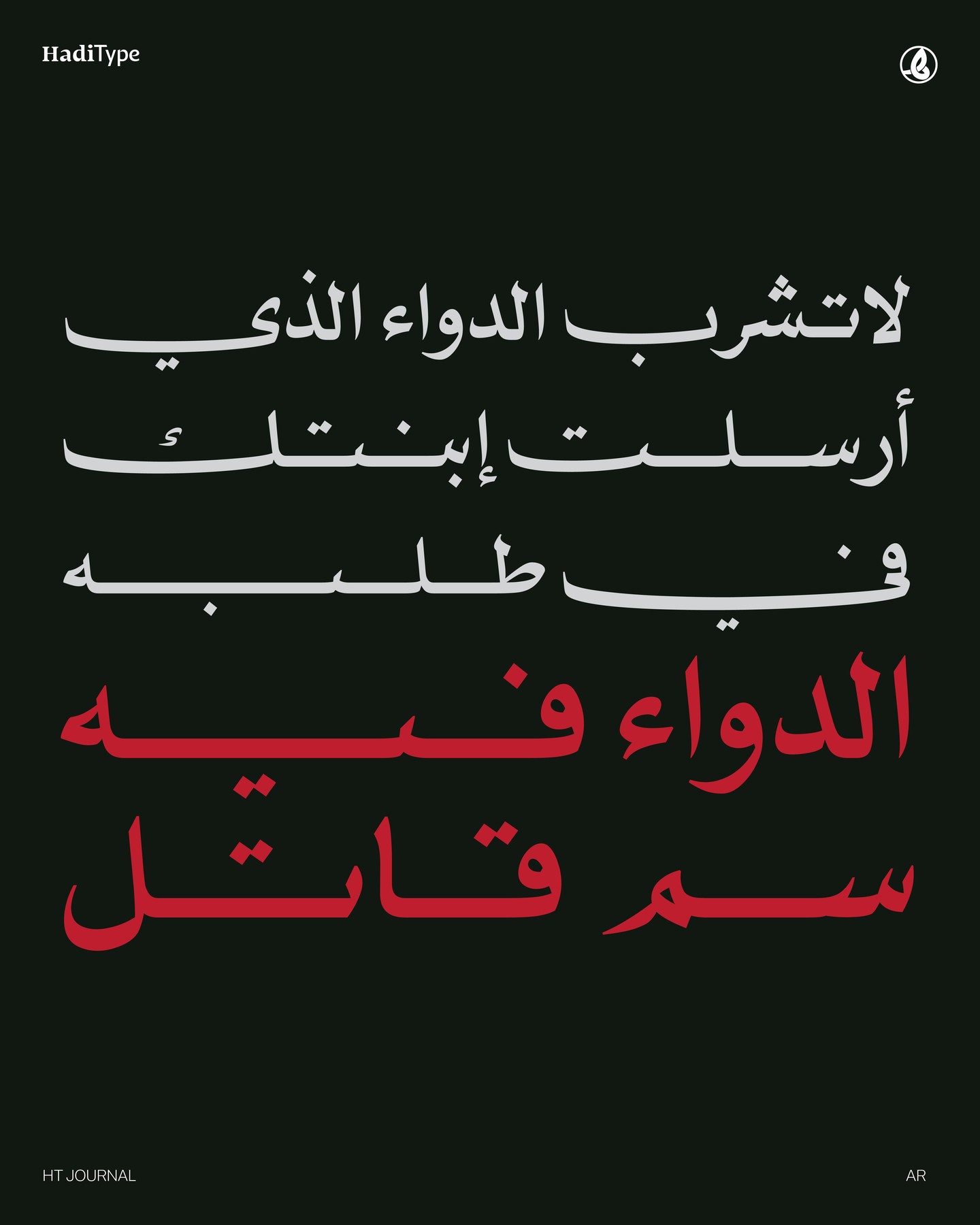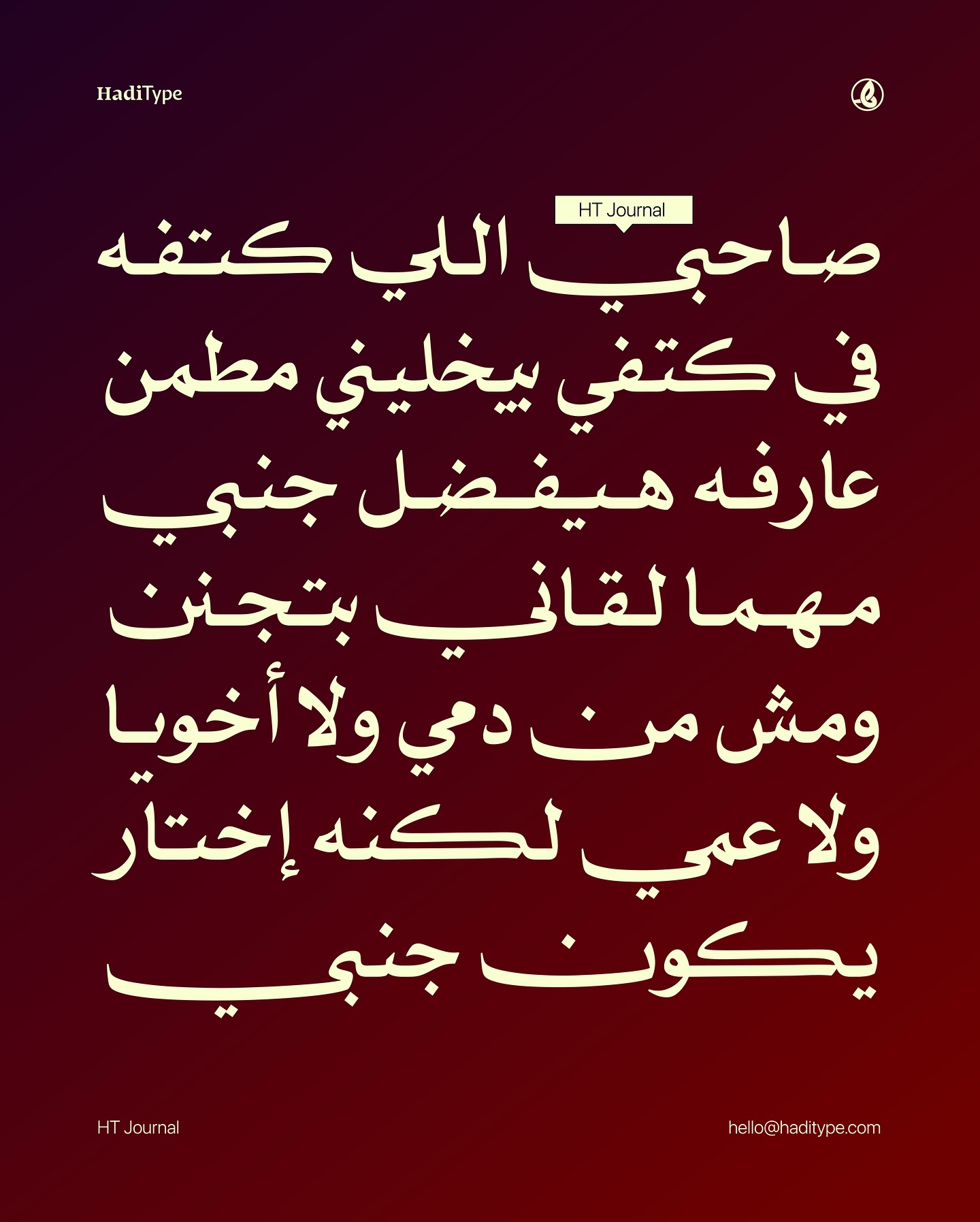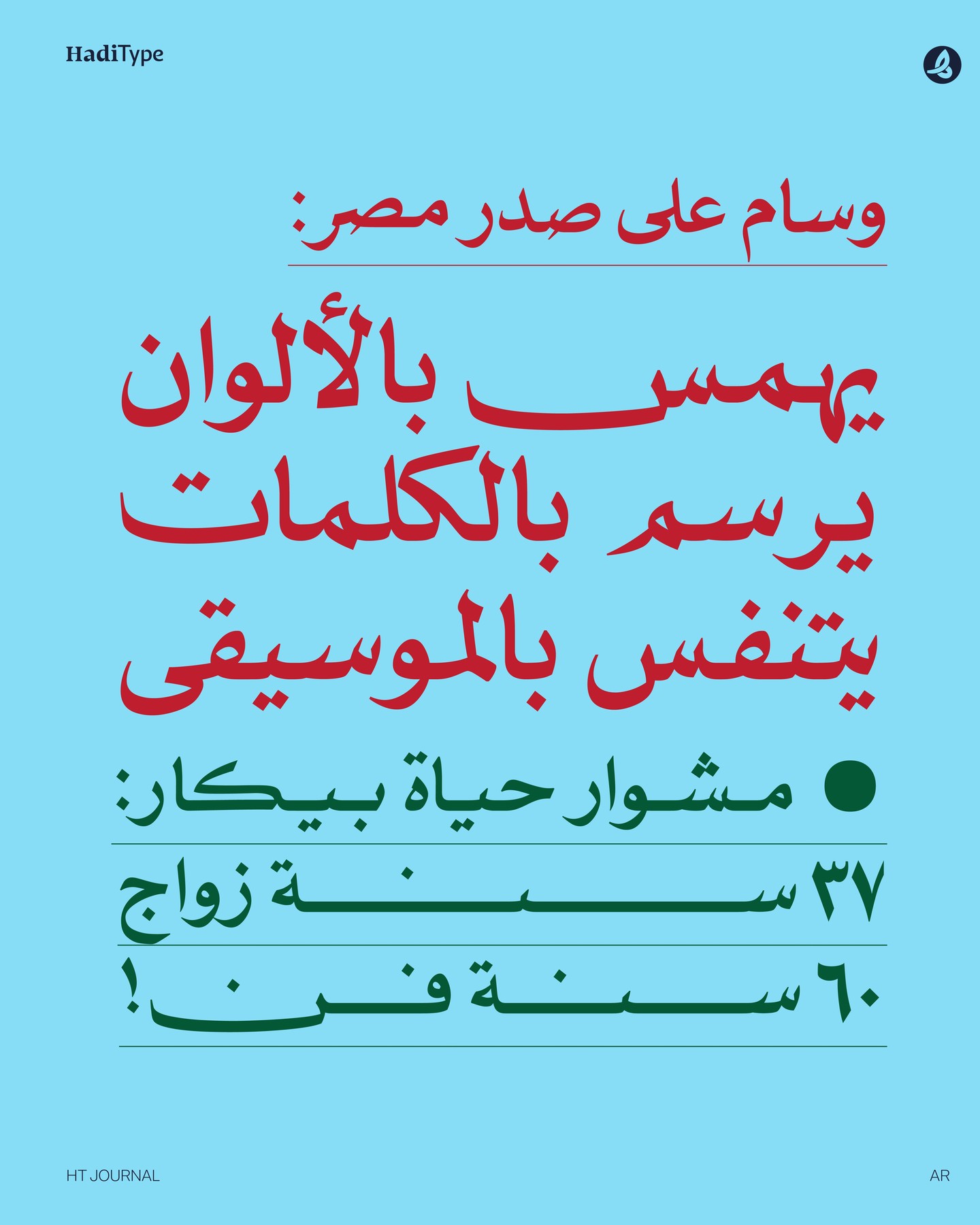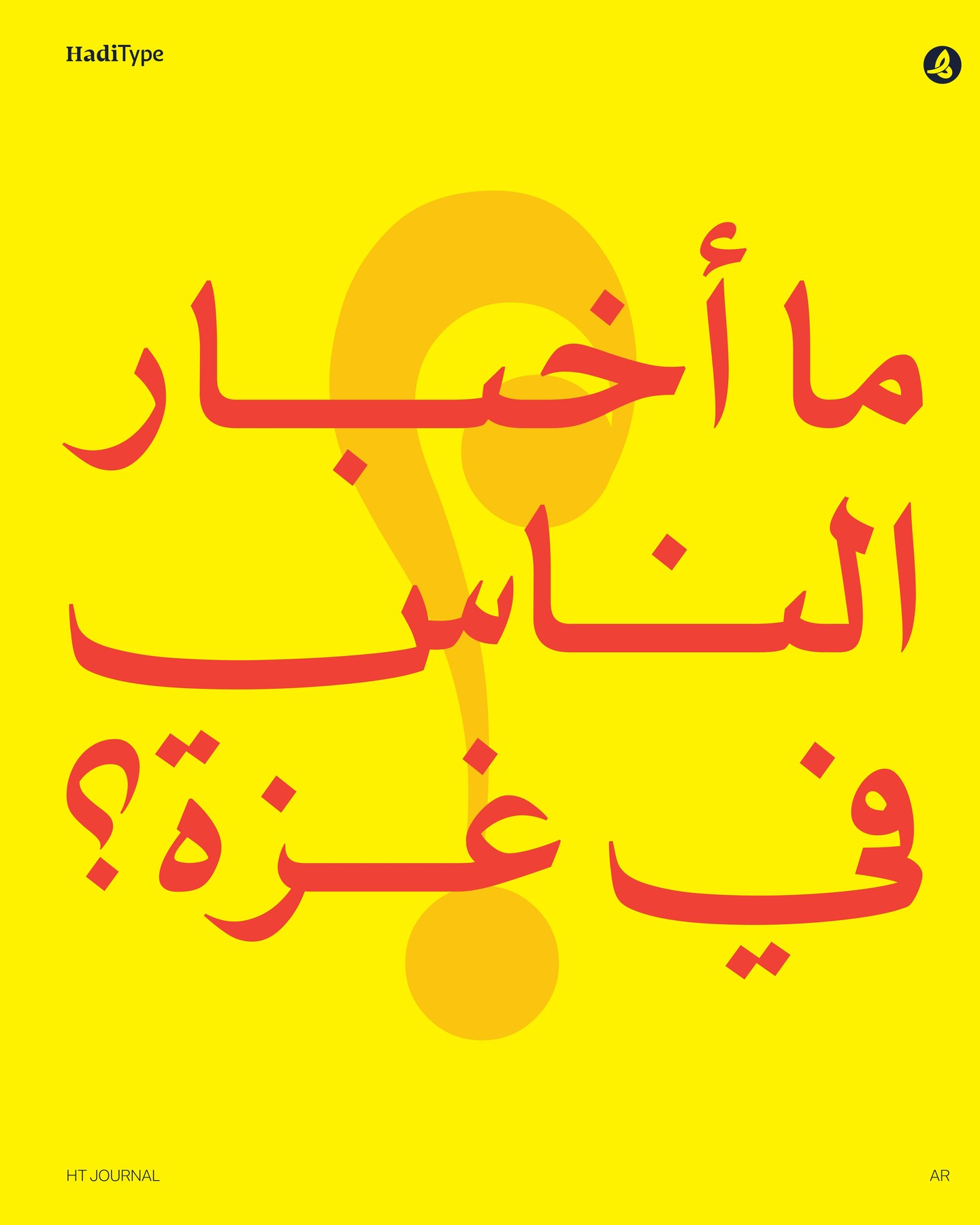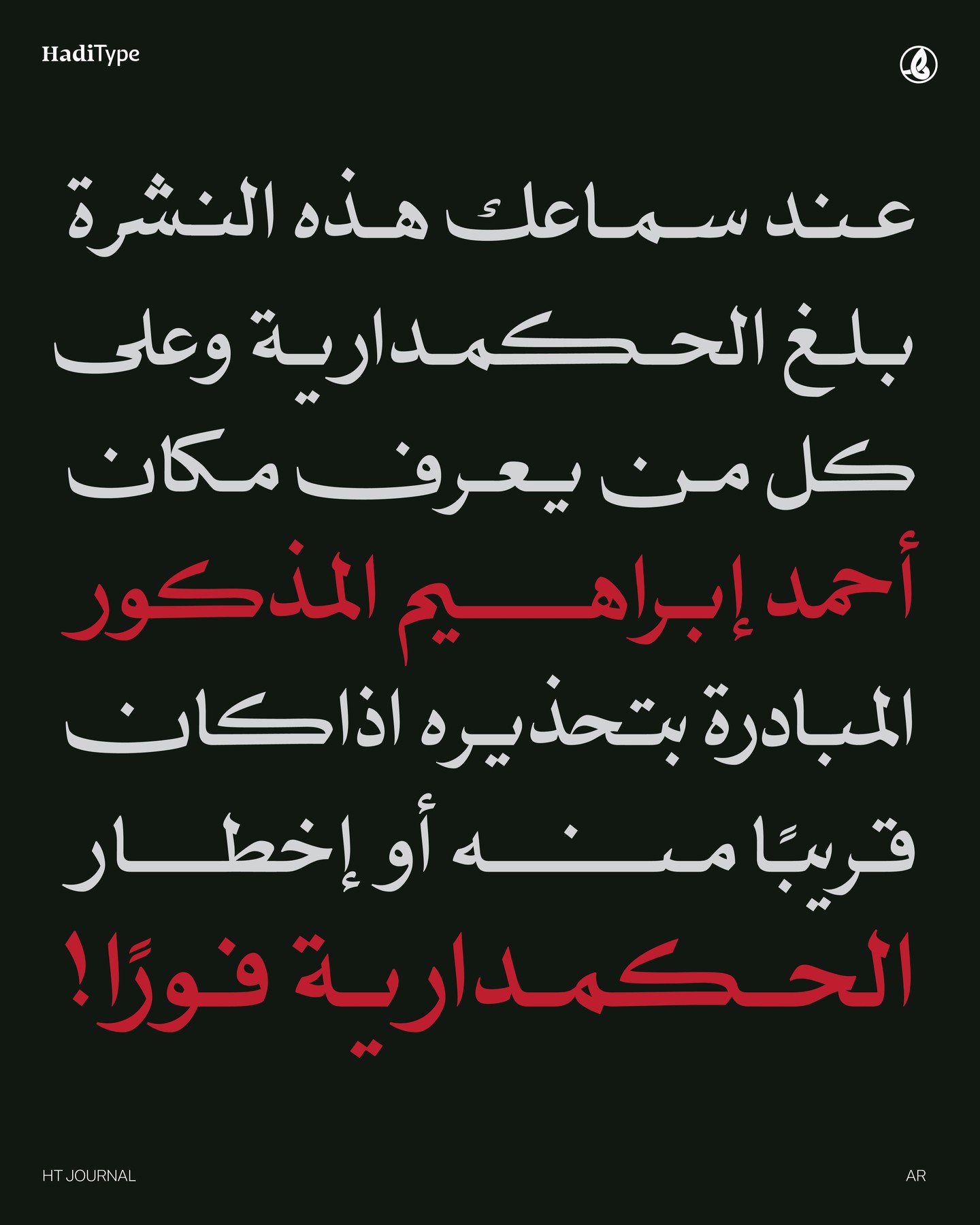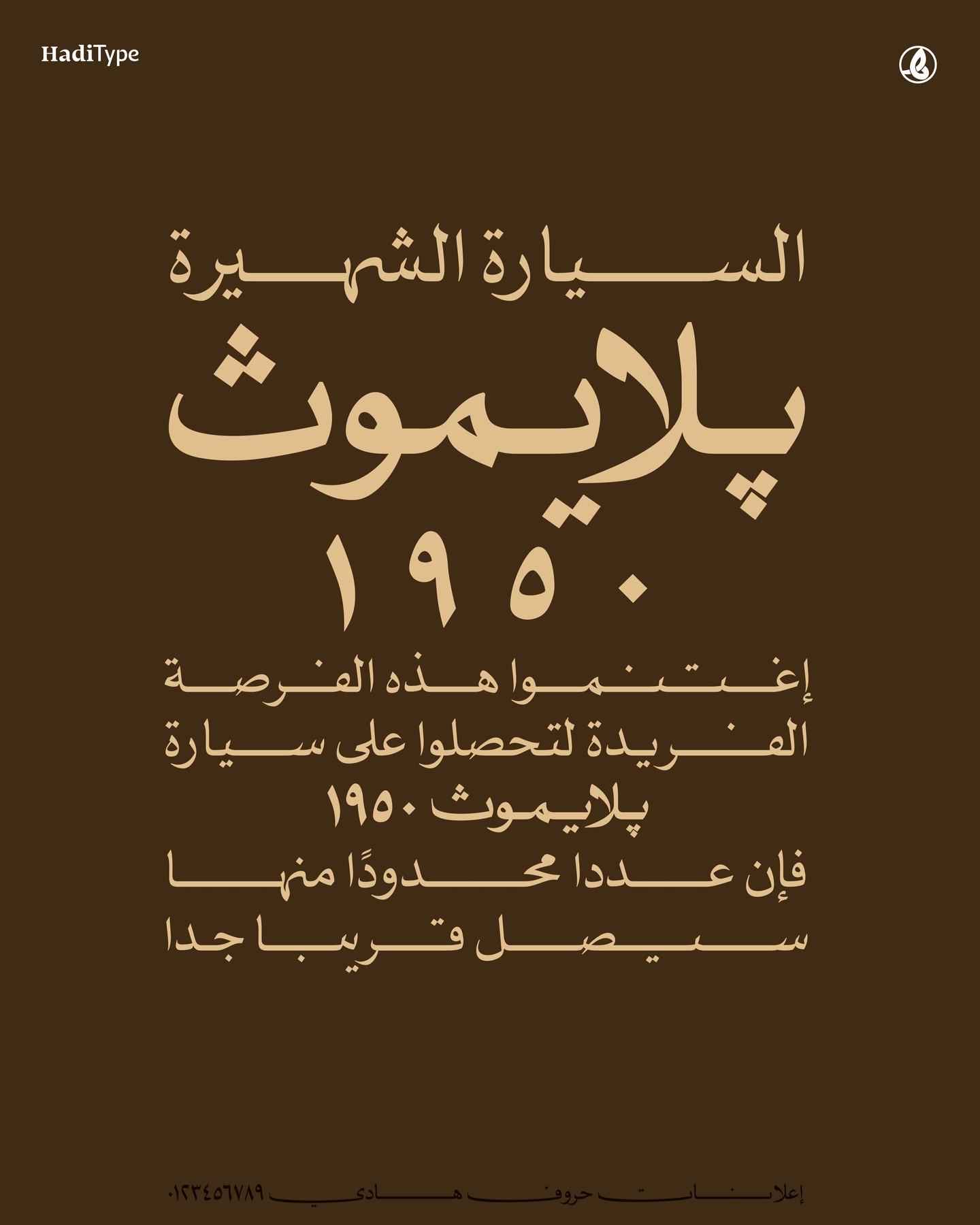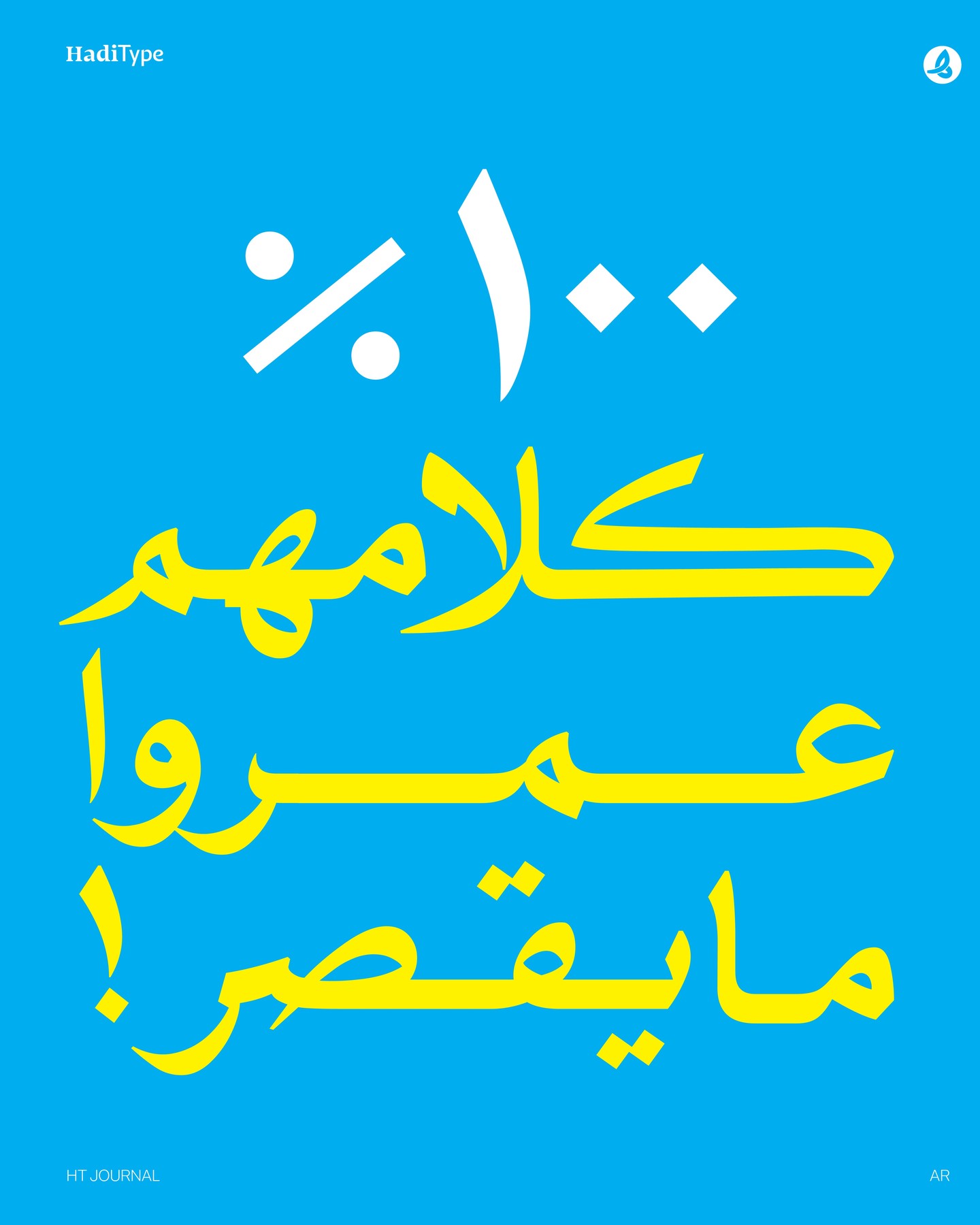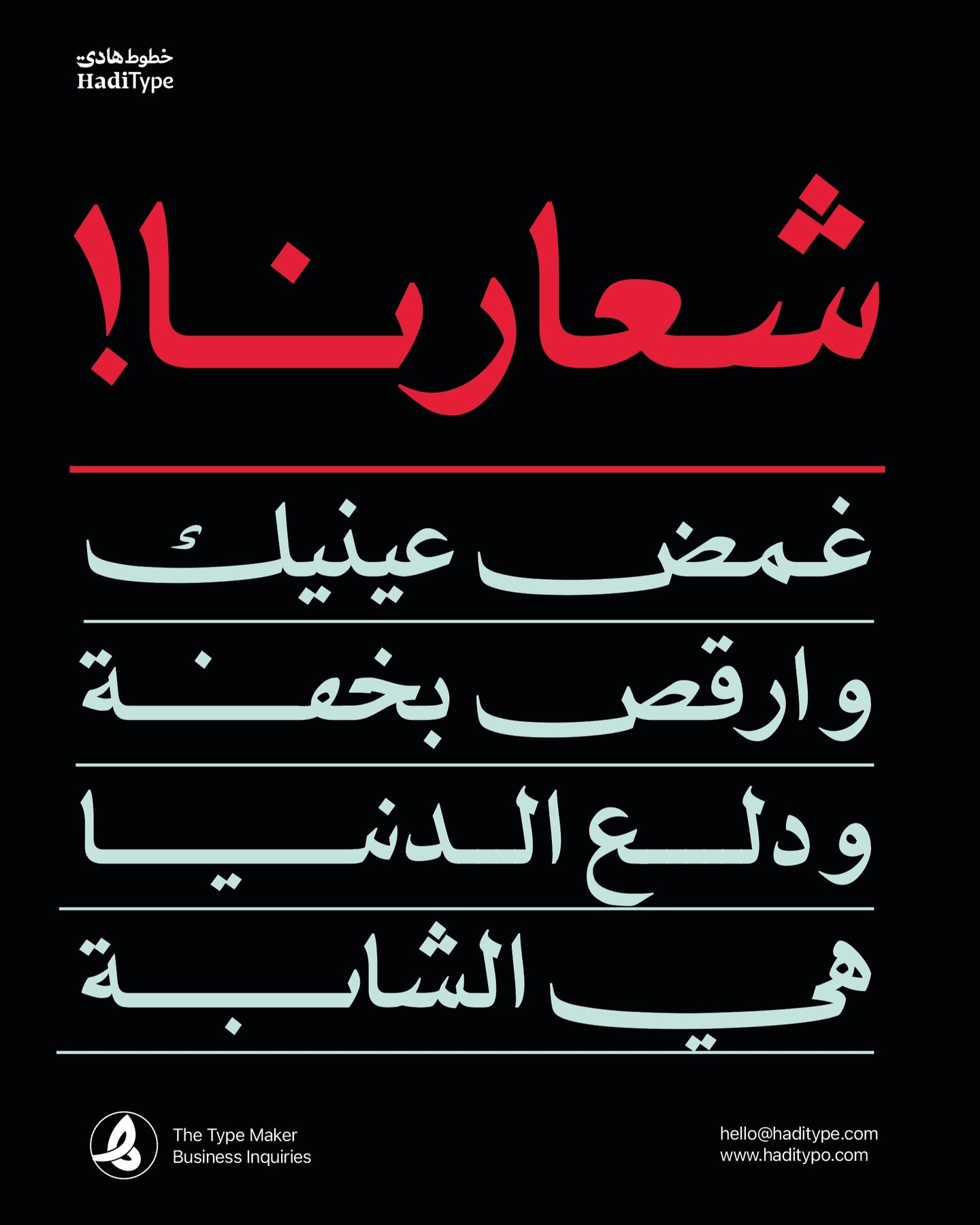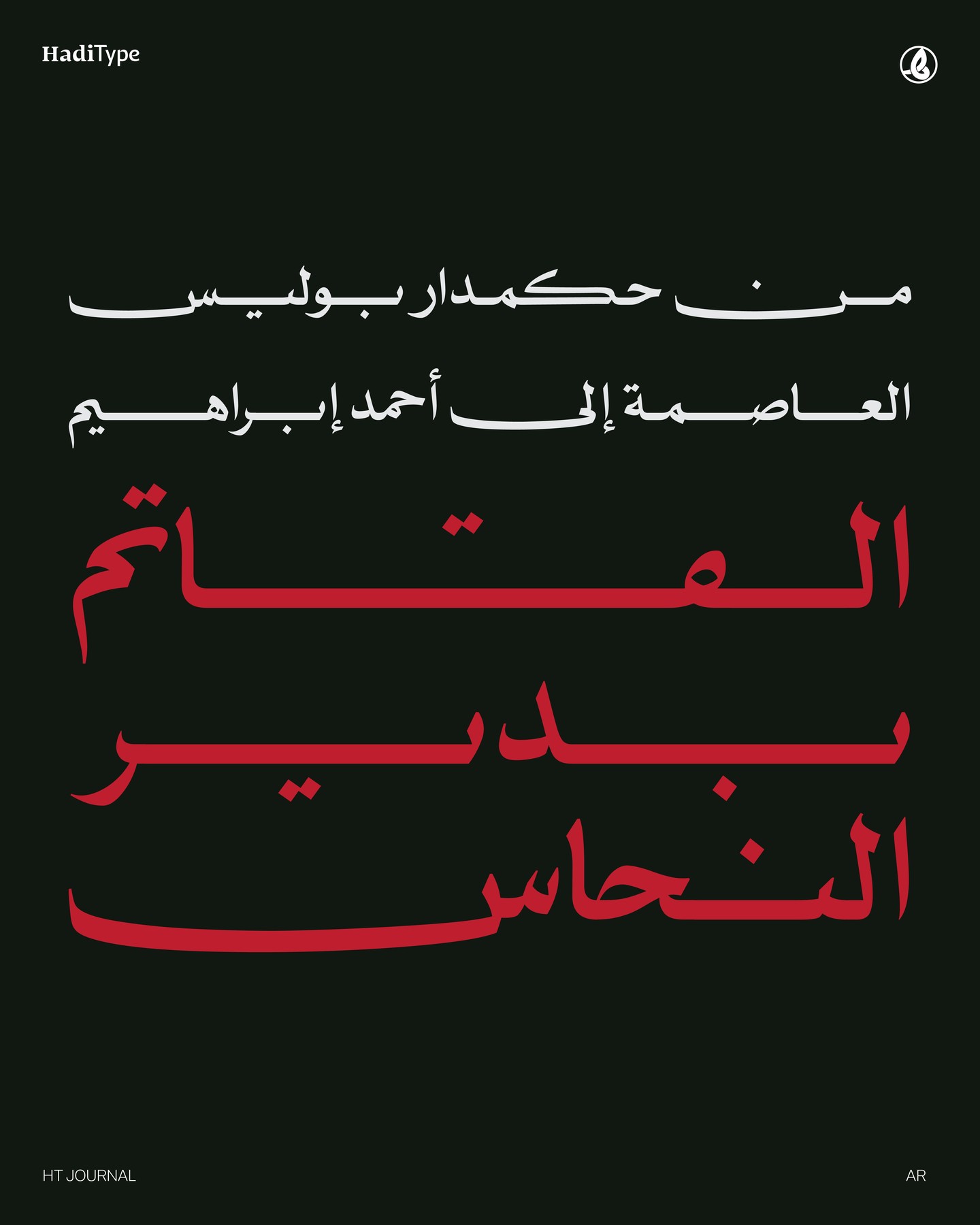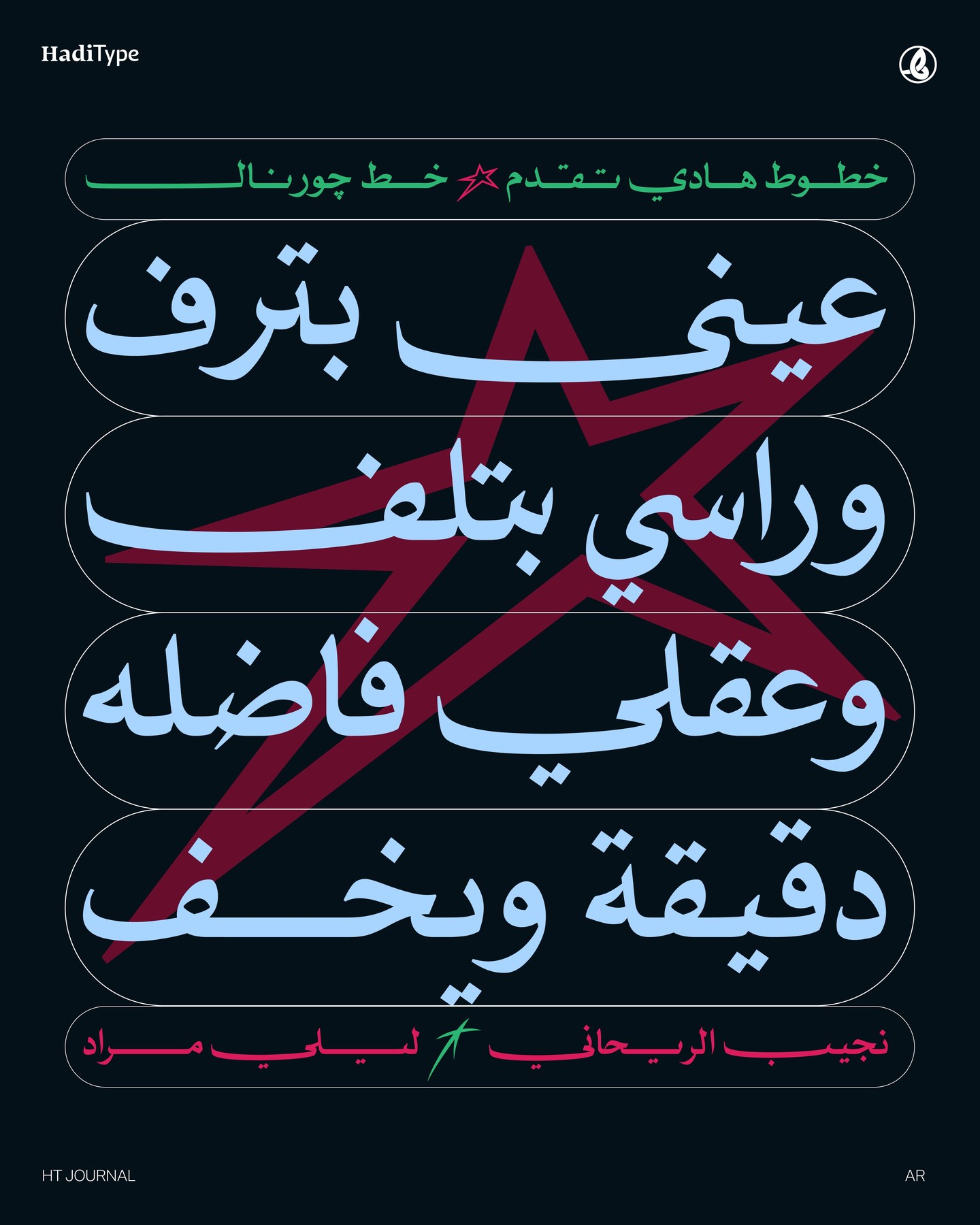
HT Journal
كل خبر يبدأ بجورنال
حروف تشبه الصحافة الكلاسيكية
جورنال – توقيع الحرف الصحفي
روح الجريدة في تصميم حديث
خط عربي مثالي للعناوين التحريرية، والمقالات، وصفحات الرأي
وضوح على الورق، وهيبة على الشاشة
مزيج بين تقاليد الجريدة ولمسة العصر الرقمي
"HT Journal" is a new Arabic font inspired by distinctive newspaper headlines in Egypt from the 1960s to the 1980s.
The font comes in a single weight and utilizes variable font technology to achieve unique diversity among various transmitted characters.